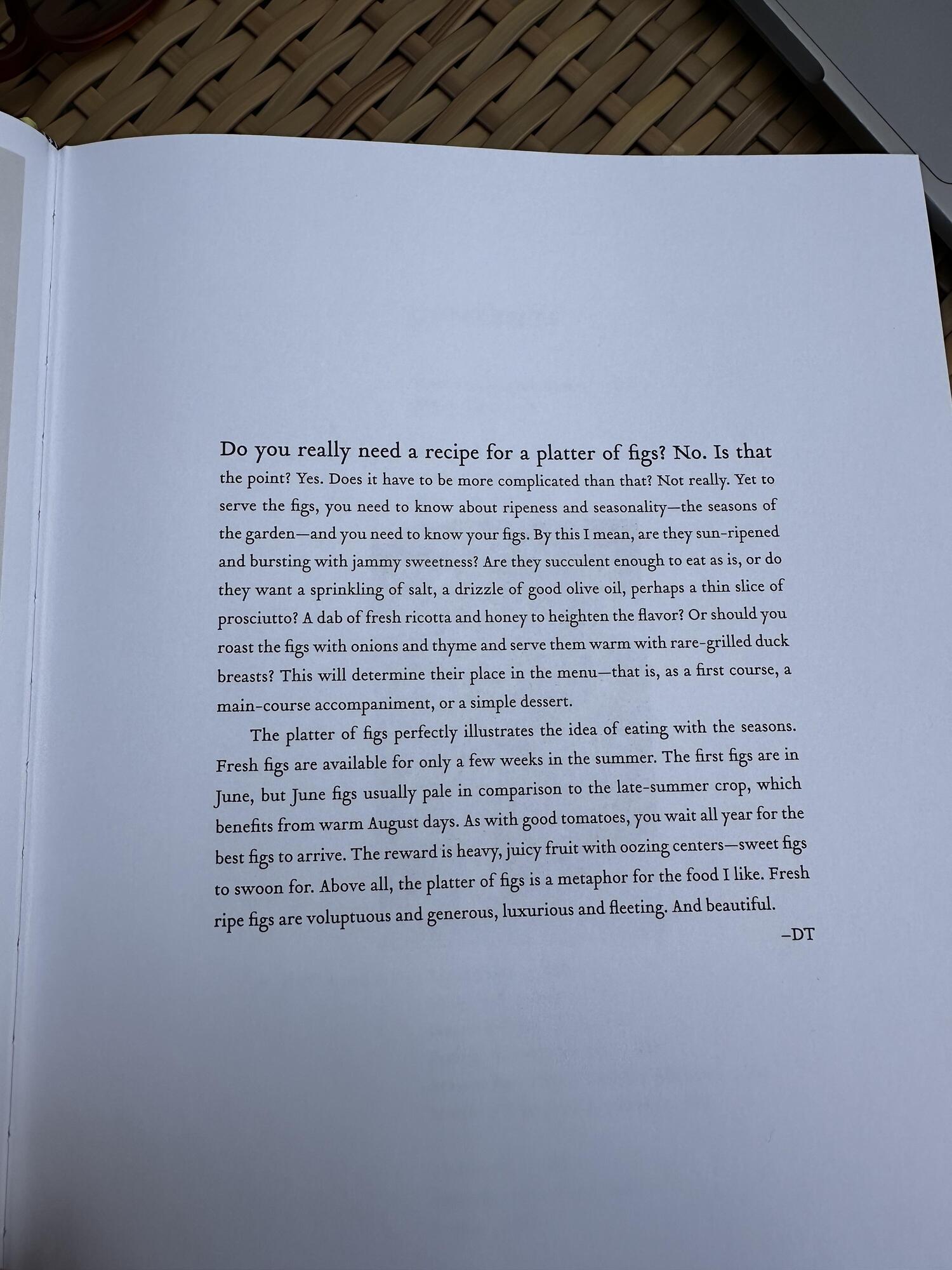
Kochbuch Typographie
Hallo, ich suche diese Typographie für ein Kochbuchprojekt.
Buch: A Platter of Figs and other Recipes, David Tanis, publiziert in den USA 2008. Publisher ARTISAN Enterainment.